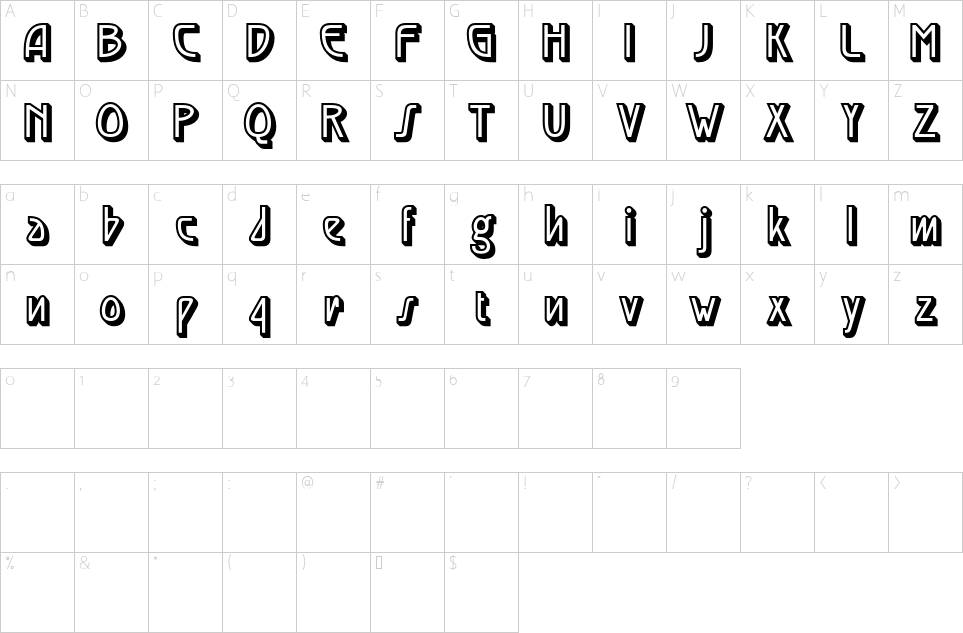
Jacelon Font – Download Grátis
A Jacelon é uma fonte elegante e sofisticada criada pelo Craft Supply Co. Desenvolvida para aqueles que procuram estilos consistentes e limpos, esta fonte oferece um equilíbrio perfeito entre letramento e legibilidade. Sujeitável a gráficos de revista ou design editorial, a Jacelon é uma escolha inteligente tanto para designers profissionais quanto para iniciantes. Com seu design meticuloso e estilo minimalista, essa fonte se adapta bem a diversas mídias digitais e impressos. Desenvolvida especialmente para os amantes de gráficos gratuitos no Windows e Mac, a Jacelon oferece uma opção pura e não adulatória que você pode usar sem compromisso. Recomendamos experimentar esta fonte para adicionar um toque único à sua próxima peça gráfica.